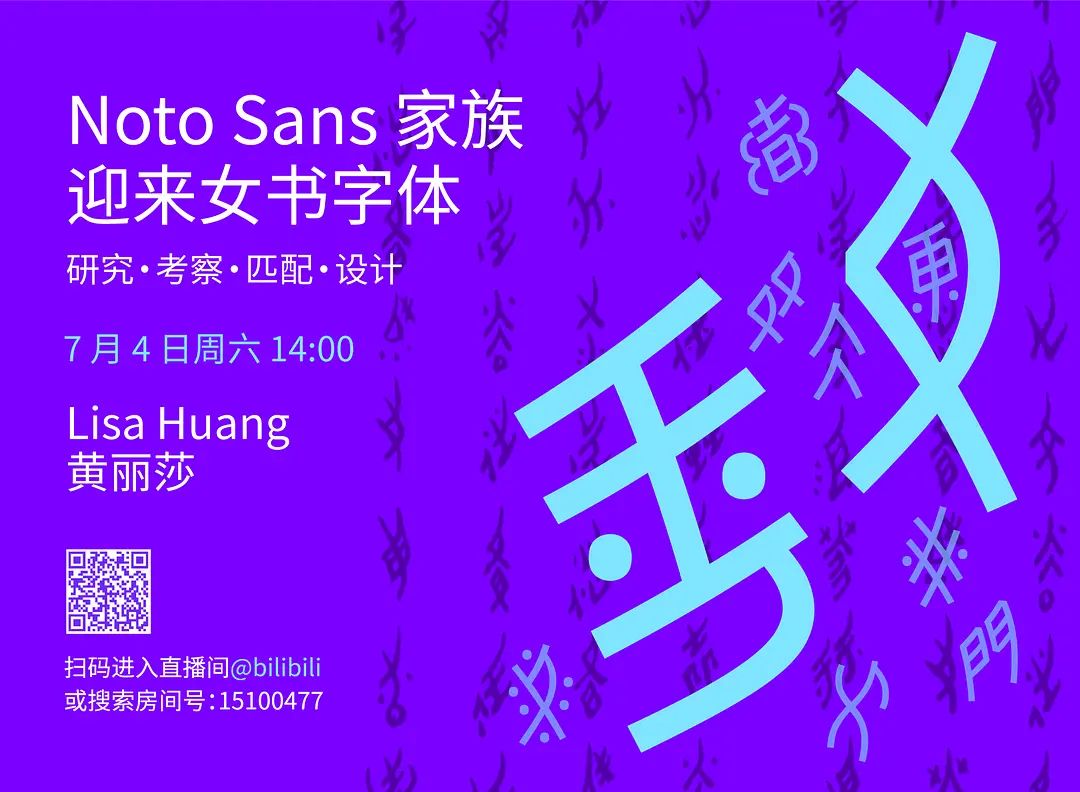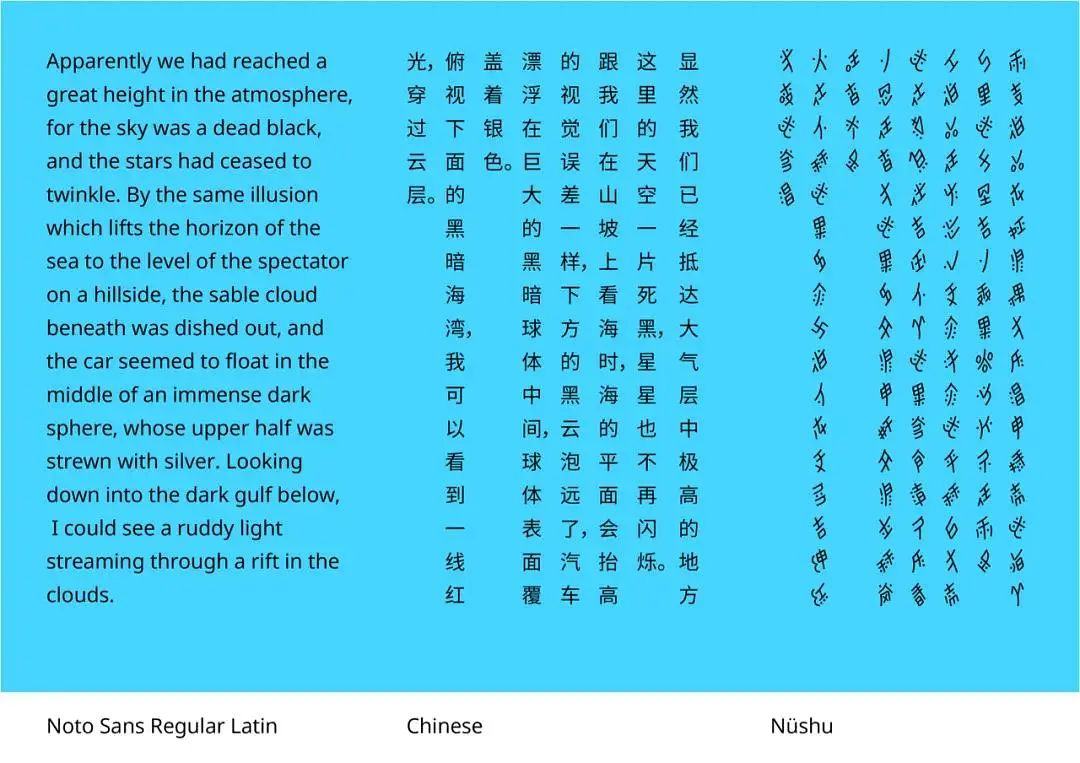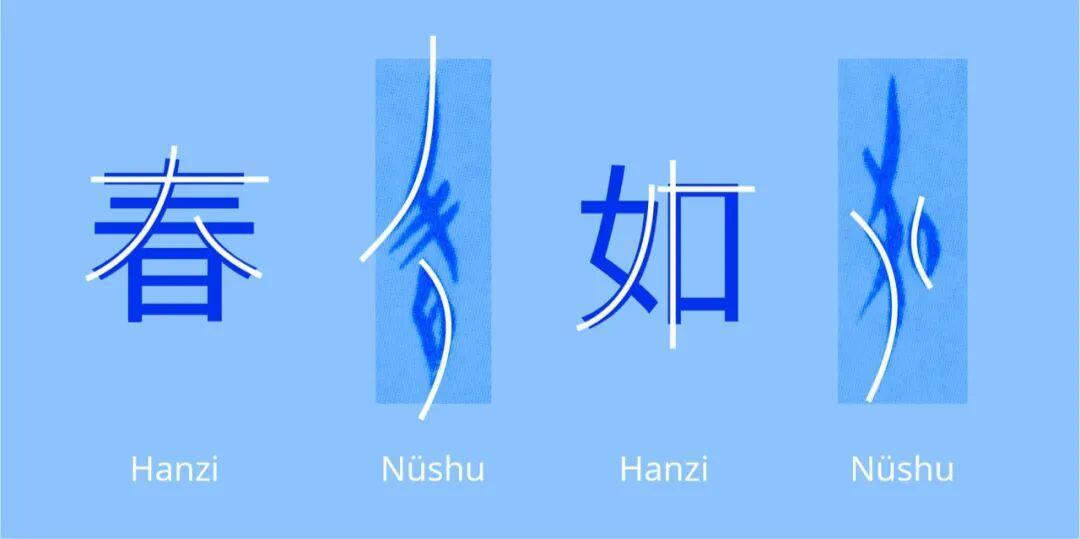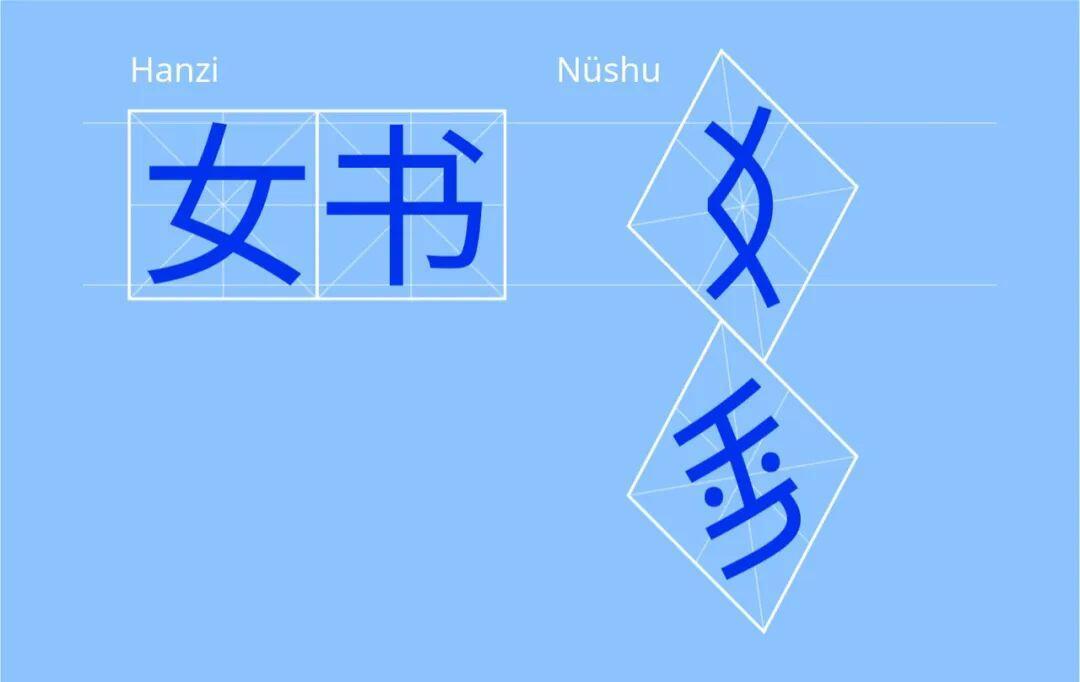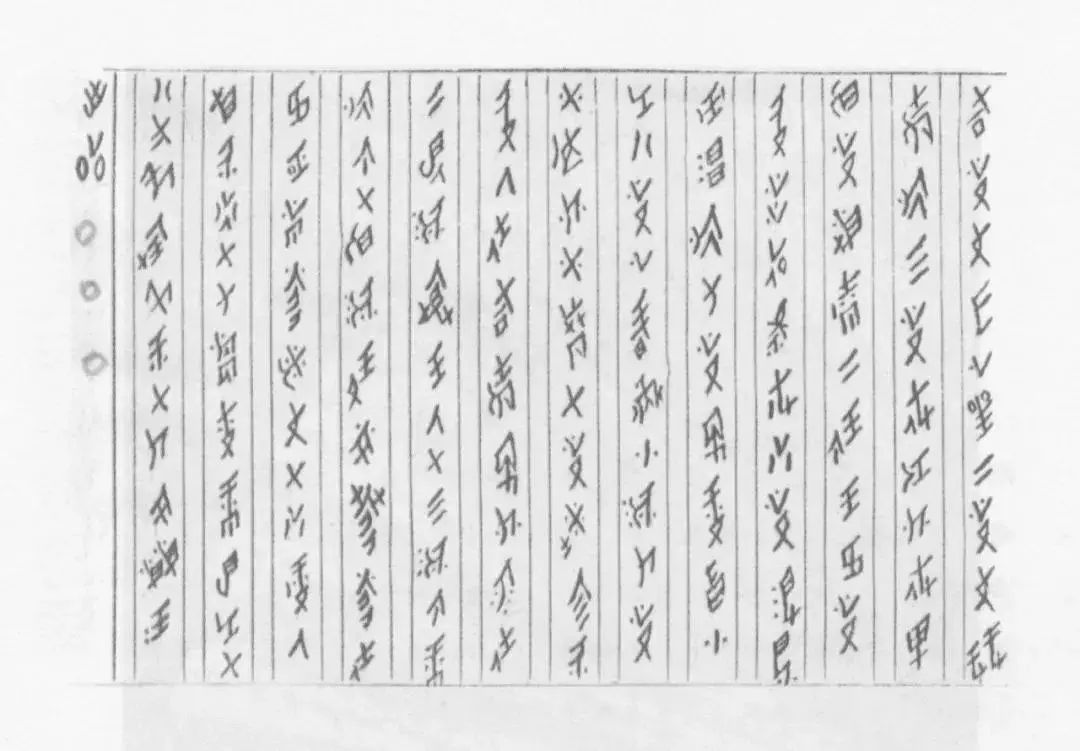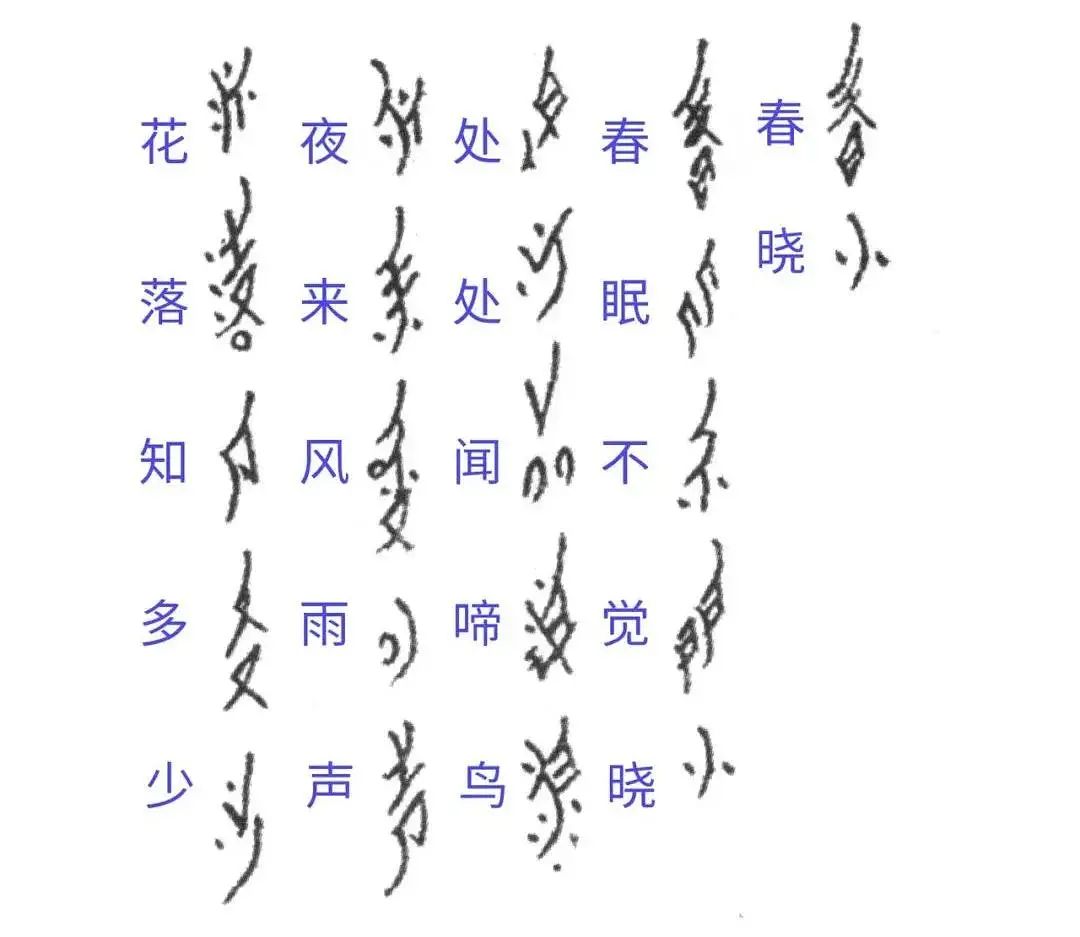
“女书”是世界上独一无二的女性使用的文字书写系统。因百年来仅流传在湖南省江永县及其近邻一带妇女中,又名“江永女书”。它用于书写湘语土话,靠母传女、老传少,一代代向下流传。女书最初的发明使用者在性别歧视而不允许接受教育的条件下,发展出自己的独立文字体系,成为人类历史上一个神奇的文化现象。
自上个世纪八十年代开始,通过几代学者的努力,这种罕见的女性字符才逐渐被世界所了解和关注。中国政府也开始重视保护女书,并于 2006 年将其选入第一批“国家非物质文化遗产名录”。2016年,对文字系统进行编码的万国码联盟正式确定将女书加入 Unicode,并随着之后的 Unicode 10.0 版本正式发布。不过,虽然标准确定了,我们还是缺乏一款经过设计、能够在屏幕上应用的女书字体——直到三个月前,法国华裔设计师黄丽莎完成了匹配思源黑体(Source Han Sans/Noto Sans CJK)的 Noto Sans Nüshu 字体,这也是全球第一套完整的正文用女书字体。
本周六下午,我们请黄丽莎来到 3type(三言)直播间,为我们讲述她是如何为思源黑体家族匹配设计女书字体的。为了能够准确而自然地设计出女书字体,尽可能忠实于原文字的形态,黄丽莎前期做大量研究,还远赴湖南江永女书博物馆,查阅女书文本,接触练习女书的当地妇女,听取她们的经验和意见。本次字播,黄丽莎将分享她受到谷歌的合作邀请,为 Noto Sans 家族匹配设计女书的经历。
《一岁女,手上珠》,高银仙 (1902–1990)书写。
孟浩然《春晓》, 何艳新 (1940-)书写。
女书的使用
女书是一种表音文字,每一个字代表一个音节,用于记录当地的方言。女书语言系统就像日语的平假名或片假名一样,当方言中具有相同发音时,往往用一个字符来表示,而一个字符又可以表达多种含义。这种特殊性使得女书所需的字符集大大少于表意的汉字,但读者也只有在明白方言和上下文的情况下,才能理解用女书编写的文本。
女书的特征
女书独特的外观让不熟悉它的人引申出了很多诡谲的故事和传说:女间谍、女巫、神灵或超自然生物的文字……但很明显的是,创造和发展女书的女性从周遭的环境汲取灵感,许多女书字符甚至是一些变形的汉字,再加上一些其他的字符。
汉字具有占据相对较大空间的笔画作为结构支撑,多种笔画延伸方向和书法笔触造成的笔画对比度,而女书在某种程度上要简单得多。它没有严格的垂直或水平笔画,只有弯曲的对角线和直线(圆也是由两条曲线组成),大部分都向左转,没有标点符号,没有衬线,笔画也没有很强的粗细对比。
汉字的笔画可以向各个方向延伸,而对于女书而言,它的笔画主要是向左和向下弯曲的(女书是垂直书写和阅读的,遵从传统中文从右至左的书写顺序)。对于女书而言,平衡也是重点,但区别在于字符整体呈长菱形和左侧比右侧要低的规则——左低右高。
女书字符的整体比例相对偏长,比汉字字符要窄得多。因此在为了与拉丁字母或汉字字符保持相同易认性的时候,它们往往超过顶部和底部的高度。
关于字体设计师黄丽莎
Lisa Huang 黄丽莎是来自法国的华裔女性字体设计师,曾在纽约进修Type@Cooper 课程,后毕业于荷兰皇家艺术学院(KABK)的 TypeMedia 专业,与 Thomas Kim 合作运营平面和多文种字体设计工作室 Polyform Studio。3type 曾约稿黄丽莎报导过她的字体设计师成长之路,详见字体设计师养成记:来自巴黎的华人字体设计师和在荷兰海牙学习字体设计。